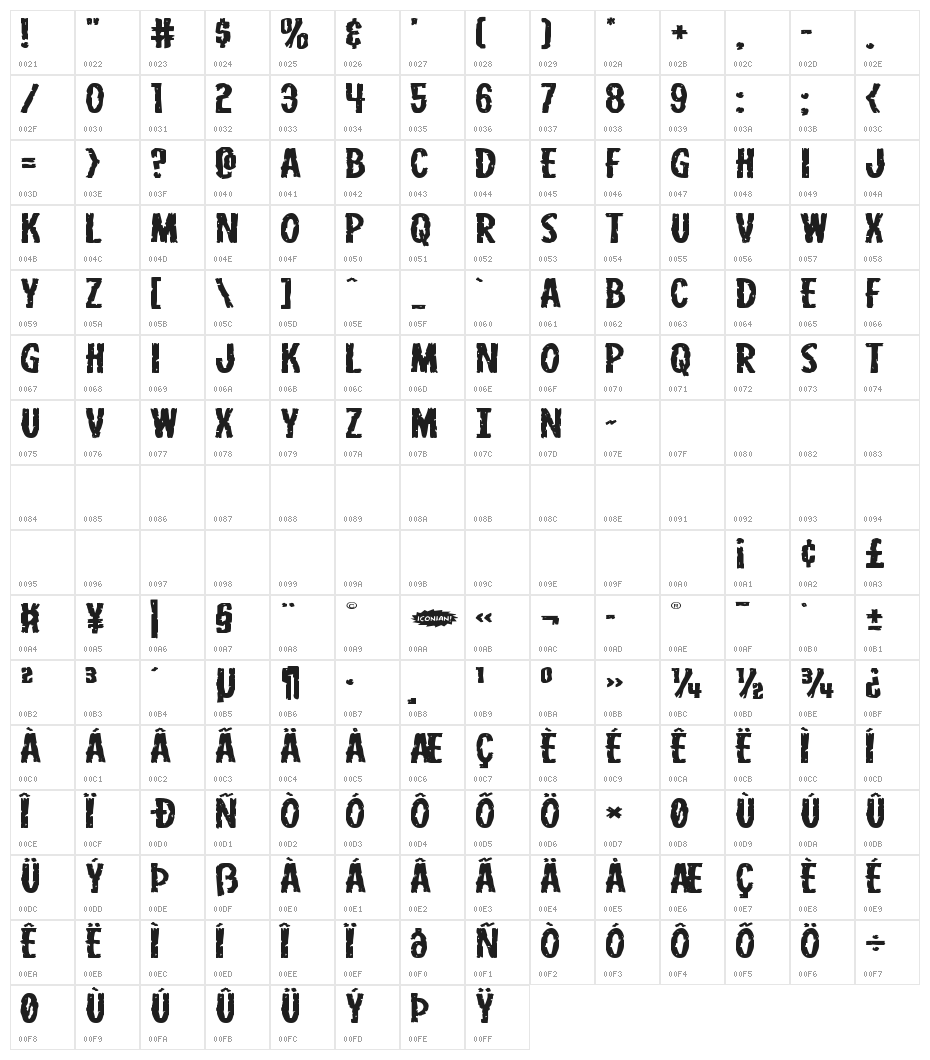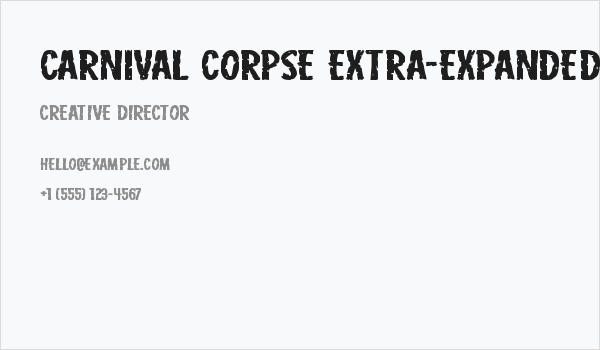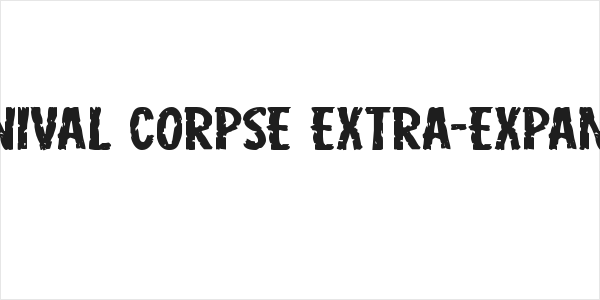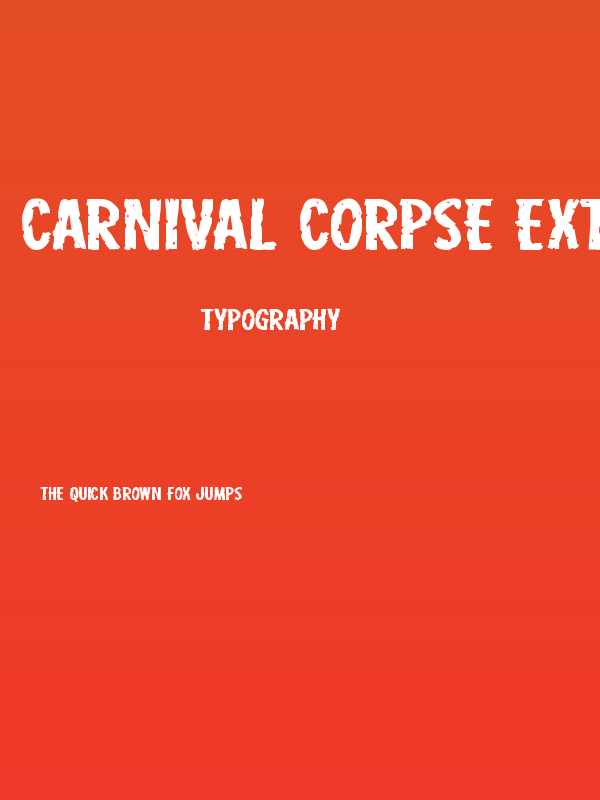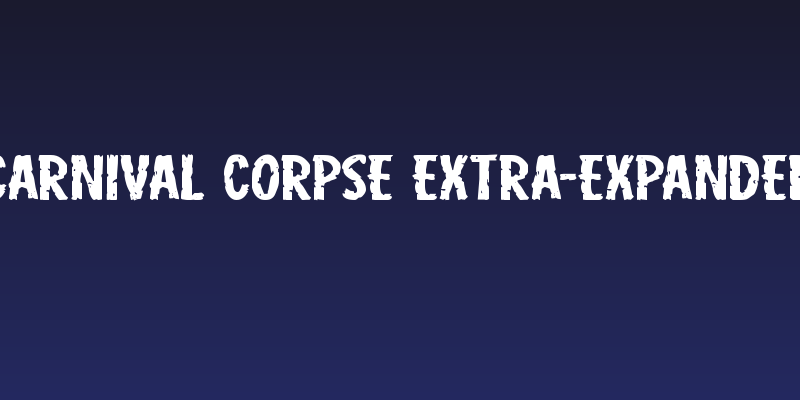
Carnival Corpse Extra-Expanded Font
| Categorie | Horror |
| Stile generale | Vintage, Decorative |
| Progetti proposti | Ideal for horror movie posters, Halloween event flyers, vintage-themed designs, and edgy branding projects. |